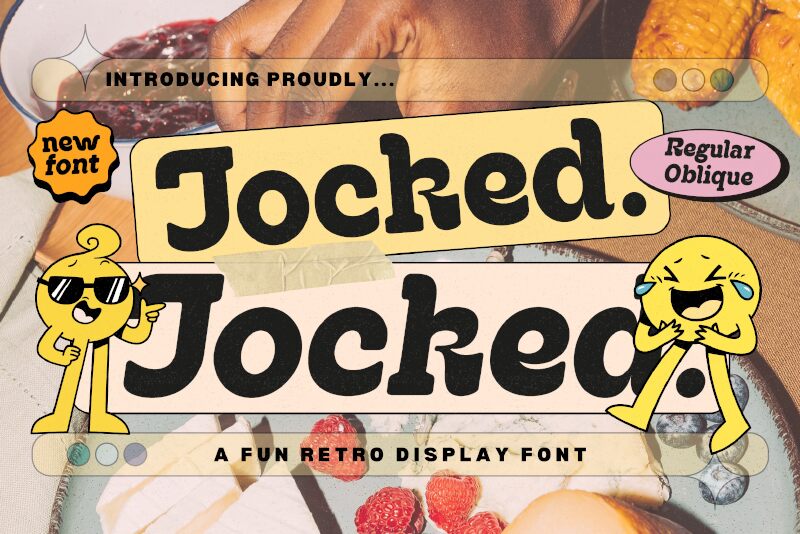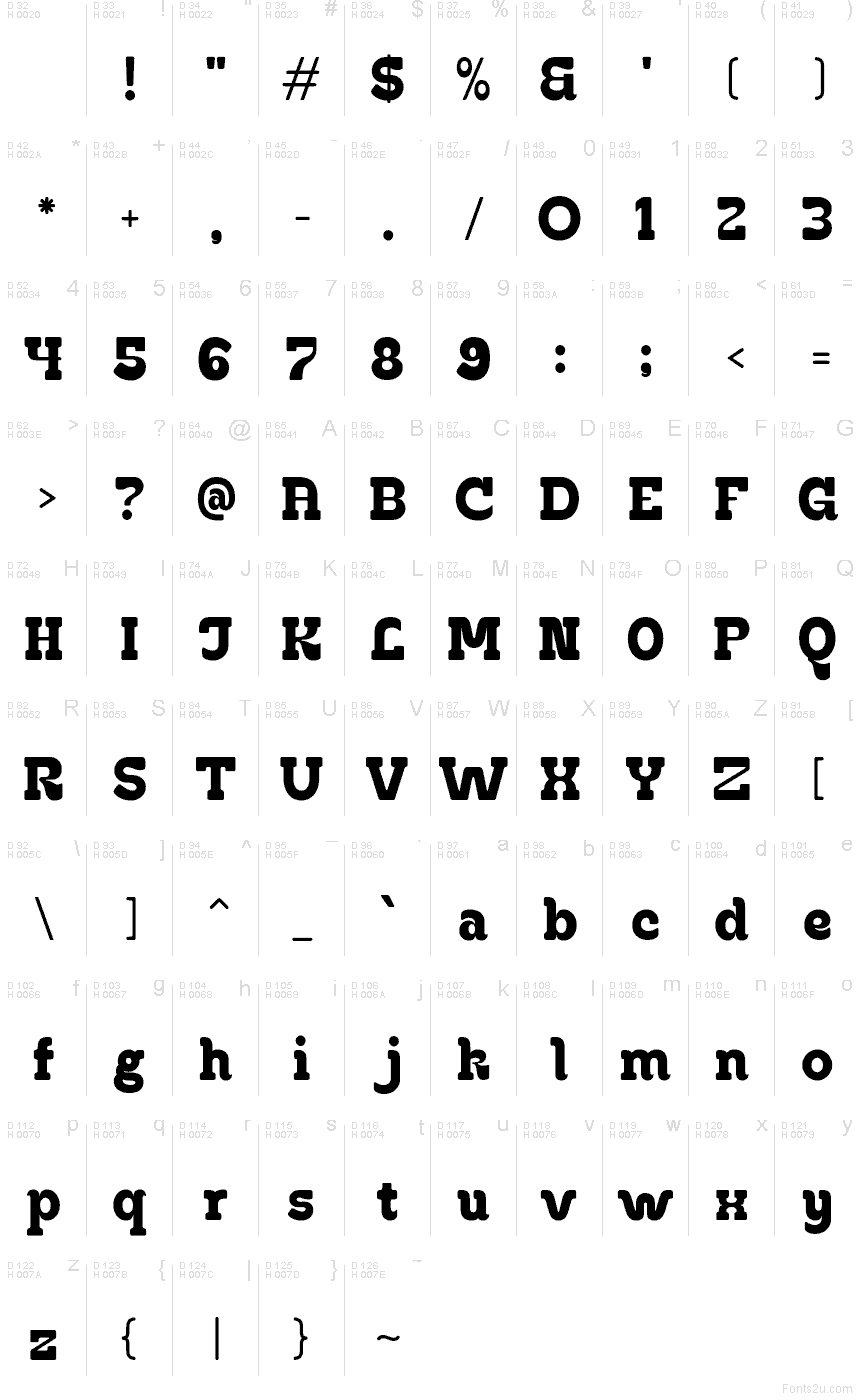
Podgląd czcionki Jocked Regular
Jocked od Glyphminds Studios to darmowy, utrzymany w stylu retro font typu display, charakteryzujący się dużymi, miękkimi krzywymi oraz masywnym, osadzonym nisko rytmem, który przywodzi na myśl opakowania i malowane szyldy z lat 70. Litery bazują na ciężkich, obłych kształtach, ale dzięki kanciastym narożnikom i blokowym łączeniom font nie staje się zbyt słodki, zyskując solidny i zabawny charakter.
To połączenie sprawdza się w brandingu kawiarni, opakowaniach przekąsek, nagłówkach plakatów, okładkach albumów, planszach tytułowych czy krótkich logotypach, gdzie darmowy font musi być wyrazisty, ale nie tracić na przystępności. Świetnie sprawdza się również w dużych, otwierających słowach i monogramach, ponieważ szerokie sylwetki pozostają zapadające w pamięć nawet w bardzo krótkich tekstach.